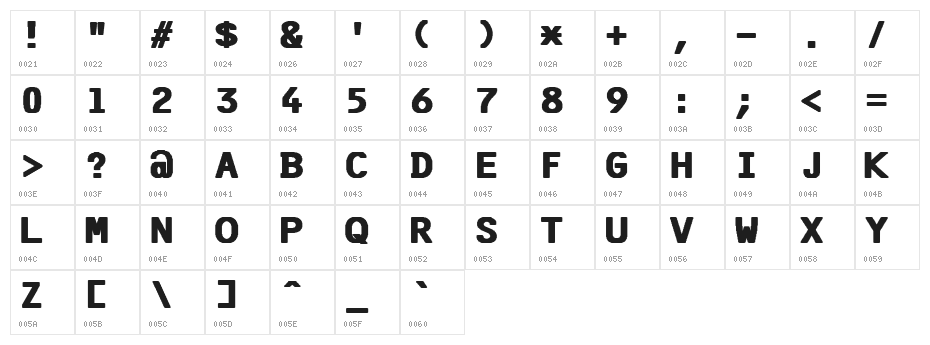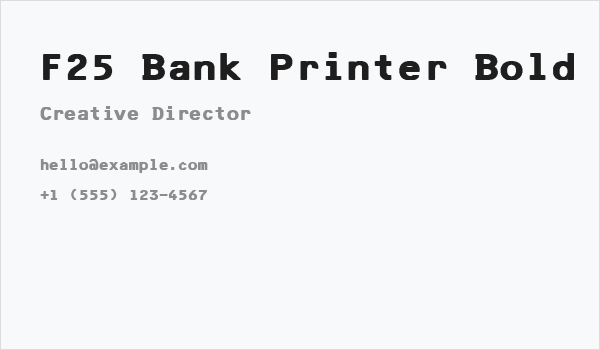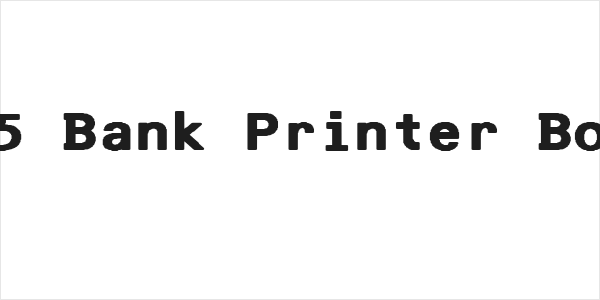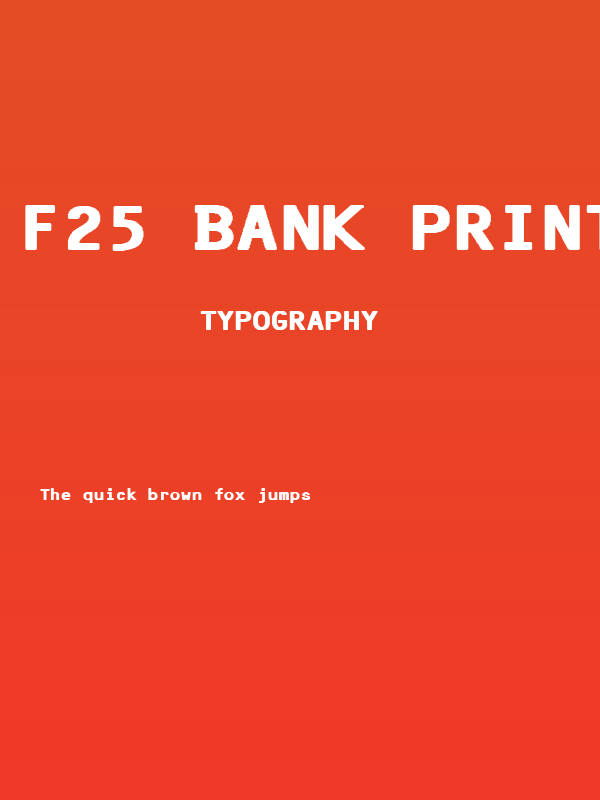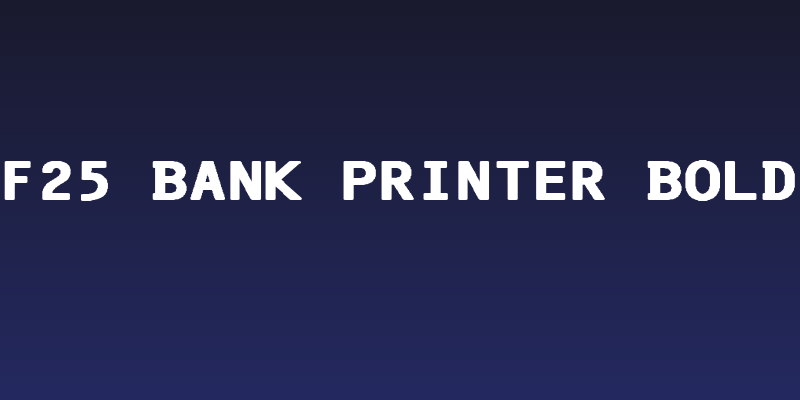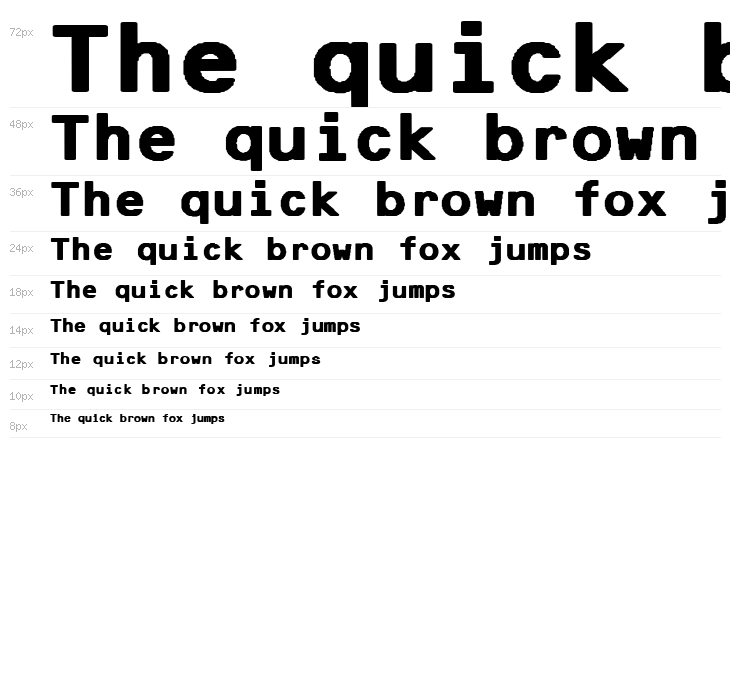
F25 Bank Printer Bold Font
| Gesamtstil | Classic |
| Anwendungsfall | Coding, Technical documentation, Data tables |
| Vorgeschlagene Projekte | Ideal for coding environments, retro-themed designs, data tables, and technical documentation. |